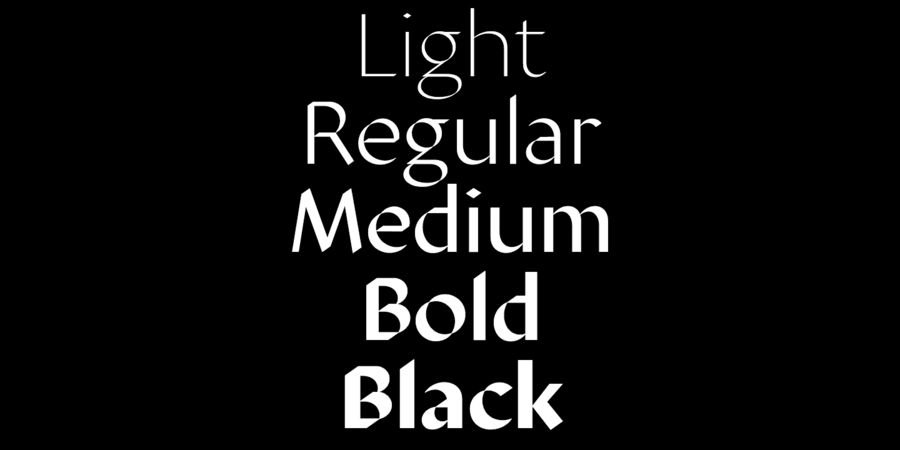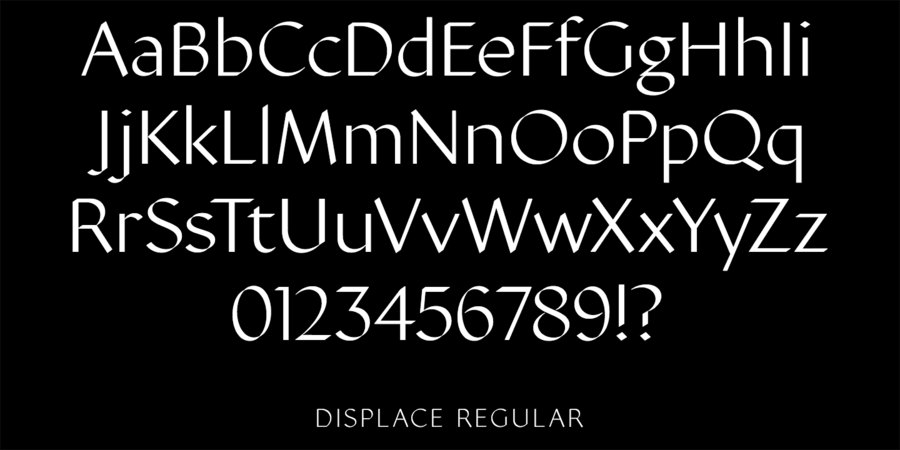
Displace 2 (5 шрифтів)
Displace 2.0 – це акцидентний шрифт без зарубок. Оригінальний гуманістичний ґротеск, базований на каліграфічному дукті плаского пера. Шрифтове сімейство налічує 5 насиченостей: Light, Regular, Medium, Bold, Black. Шрифт розробив Денис Серебряков у 2019 році.
Асоціації з сімейством шрифтів Displace 2Особистість і характер гарнітури:
тонкий, оригінальний, характерний, гострий, різкий, чіткий, міський, незвичайний, стійкий, динамічний, артистичний, дорогий, технічний, крихкий, рівний, експериментальний, сріблястий, витончений, модний, сучасний, дзвінкий, музичний, скляний, точний, благородний, красивий, майстерний, освічений, мінімалістичний, лаконічний, прозорий, пульсуючий, мерехтливий, худий, твердий, гордий, виразний, елітний, якісний, срібний, культурний, естетичний, розкішний, дорогоцінний, добірний, багатий, Простий, елементарний, логічний, холодний, серйозний, авторитетний, переконливий, архітектурний, естетський, жорсткий, залізний, сталевий, важливий, впевнений, екстравагантний, амбітний, психоделічний, важкий, сильний, яскравий, помітний, активний
Місто, мода, одяг, розкіш, дизайн, АСМР, прикраса, ювелір, коштовності, сервіровка, люкс, архітектура, годинник, музей, скульптура, меч, Трофей, нагорода, мистецтво, література, музика, срібло, преміум, парфумерія, парфуми, взуття Гарнітура має ознаки стилів: